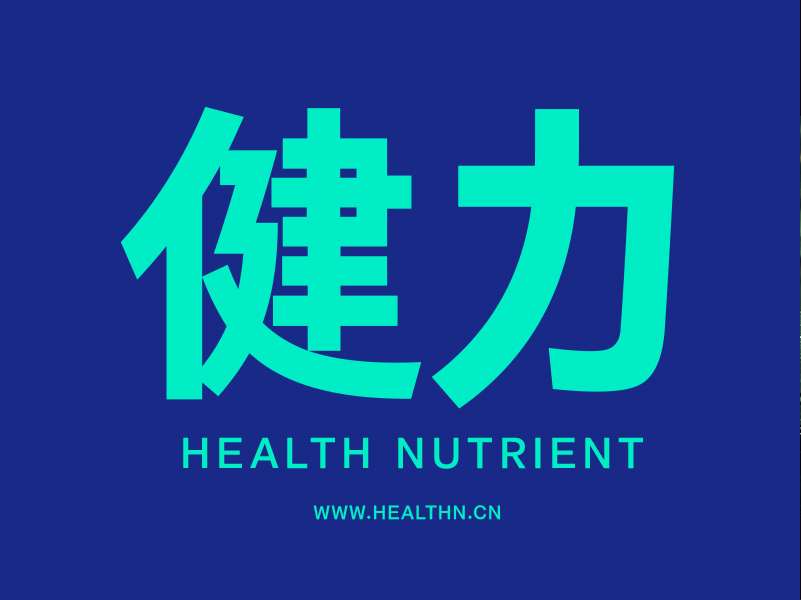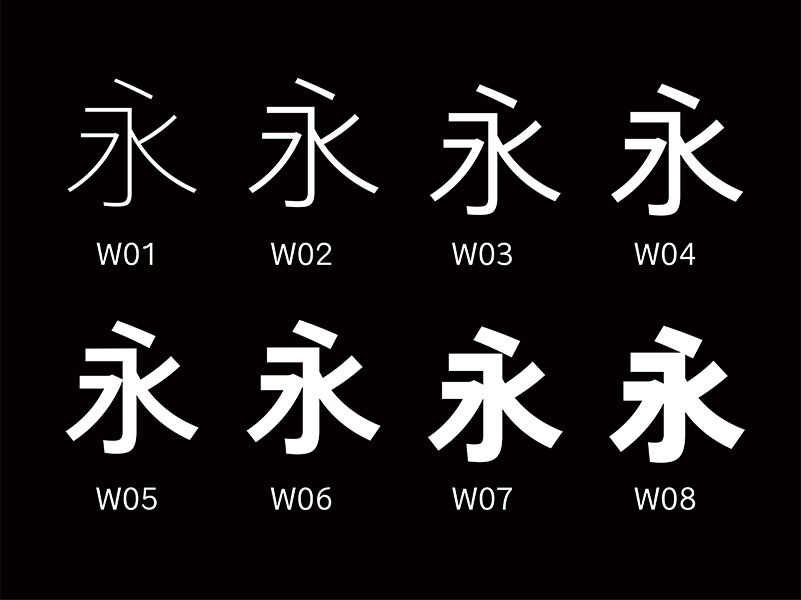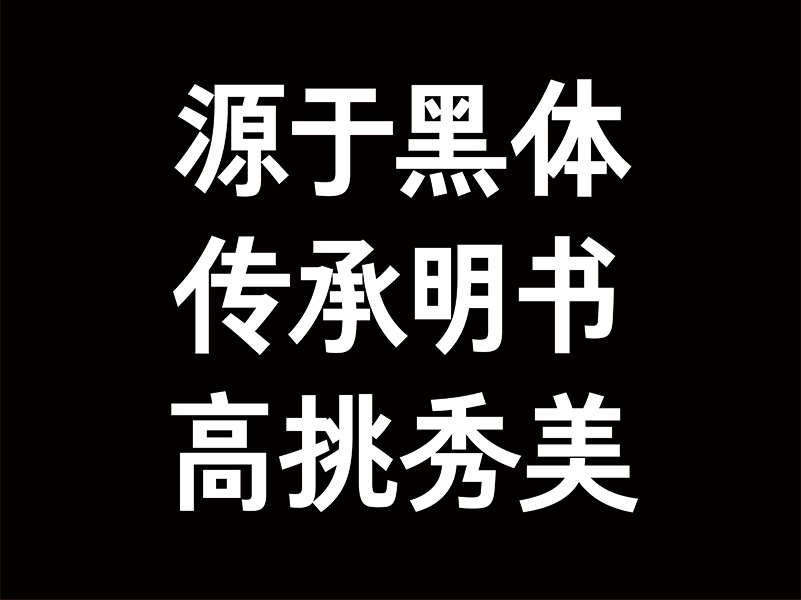
仓耳明黑 W01
仓耳明黑 W01,仓耳明黑是一套黑体家族字体,一共有8个字重,字形整体偏窄,重心略低,简洁饱满,具有块面感。看起来这套家族字体再传统黑体上做了极大的创新,以中国明代刻本中书法结体和书写为基础,字体更显高挑,相比同类产品在笔形和结构上都有独特的处理,阅读轻松的同时还更符合汉字的审美习惯。稳定坚固又刚劲有力。起笔收笔的三角形具有一定的装饰性,又使得大字重的黑体具有一丝灵动。字 体 ID:1511